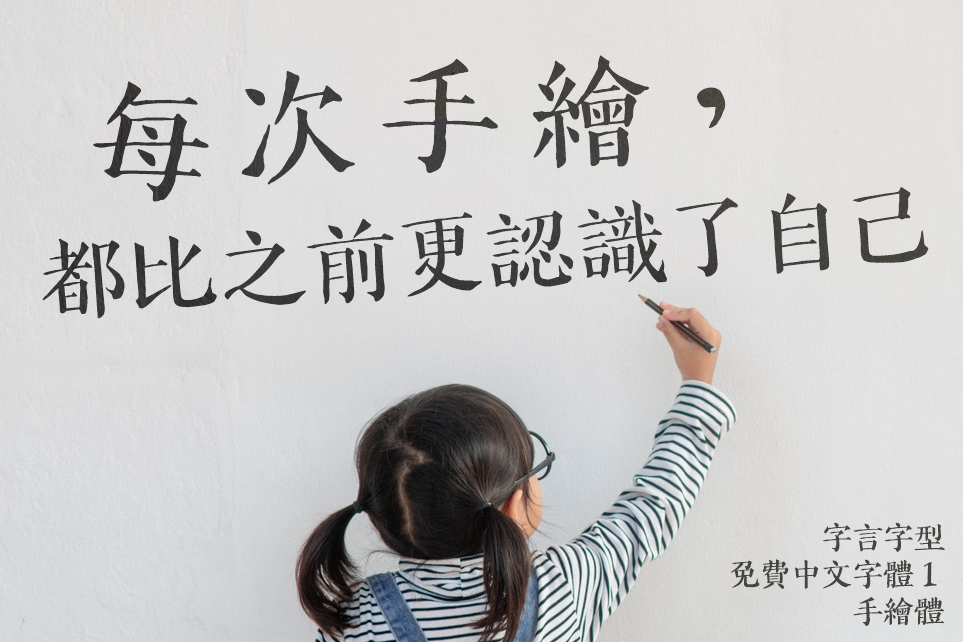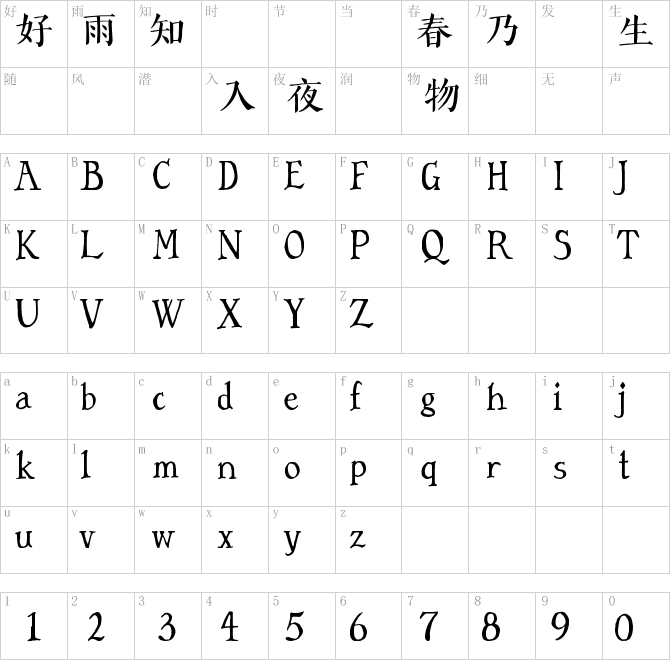
字言字型免费中文字体1—手绘体
阅读文章之前先为文中名词做出定义:
字体:文字的风格、造型。如:宋体、黑体。
字形:文字的写法。如:“玄”的第一笔是点还是竖点,幺是ㄥㄙ形还是ㄑㄙ形。
我们开发了一款要送给各位朋友的全新字型《字言字型免费中文字体1—手绘体》。这款字型采用了手绘涂鸦风格,并以宋体的笔形配上楷体的骨架制成,营造出不同于其他单一风格的造型。融合相同风格的手绘西文,包括精心设计的字距微调(Kerning)及等宽的数字等。
另外,这款字体更收录了大量的、不同于现代正体字的字形。得益于繁体字形源远流长,这些字形我们至今都可以轻松地在其他印刷字体中看到。这些字形采样自美术字、书法字、铅字字形,照相排版机字形等。
·为何采用这些字形?
我们希望除了能在文字造型上展现特色外,字形也是一可以发挥的地方。不仅是由官方机构颁布的字形,放眼望去,琳琅满目的字体以及不同的字形,这不正是多元化的象征吗?我们收录的这些字形部件,都是能够在不同的地方见到,没有一种部件是我们原创出来的。
这款字体,我们选择的字形都是不会过度影响文字辨识的字形。我们的选择主轴如下:
①极为常见的构形不同的字。比如:启/启,我们选择了启;吁/,我们选择了。
②仅需改动部件,相同部件采取一致的造型。举例:我们采样到“鬲”里面为交叉的融,我们一致修改了隔、献等字。
③选择现今更通行的字。比如我们也有搜集到“隂”,但是与今字形相去甚远,故弃之。
④字型制作者偏爱的字形。像是:出头兂(潜)、横撇的户(戸)等。
我们将这些字形放置在日常情况下能够轻松输入的事实编码上(Big5) ,来服务更多的认同我们的设计思路的朋友。此外,此字型的造型也与字形的选择相映成趣,欢迎免费下载体验!